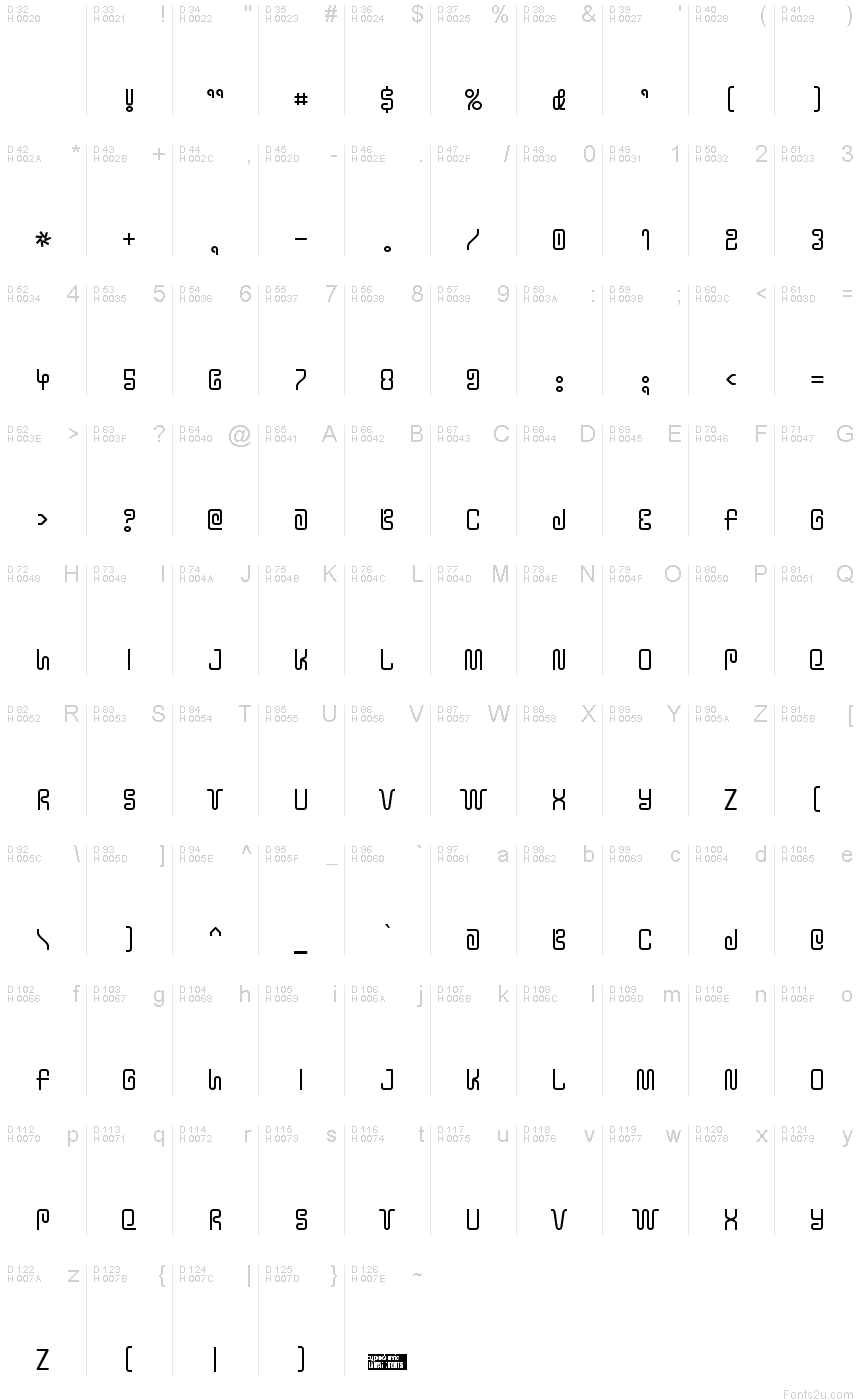
!Y2KBUG
يُعد خط !y2kbug من تصميم Ray Larabie خطاً مجانياً مستقبلياً من نمط العرض (Display)، يبدو وكأنه خرج للتو من شاشة ألعاب قديمة بها خلل تقني. تخلق ضرباته السميكة ذات الخط الواحد، ومنحنياته المربعة، ونهاياته الحلقية إيقاعاً يشبه المتاهة، مما يمنحه طابعاً رقمياً كلاسيكياً (ريترو) وفي الوقت نفسه شعوراً ودوداً بشكل غريب. تتماسك الحروف معاً بتدفق نمطي مُرضٍ، مما يحول الكلمات القصيرة إلى رموز رسومية تبدو وكأنها مبرمجة وليست مكتوبة.
باستخدام !y2kbug، تستقر العناوين في مكانها تماماً مثل عناصر واجهة المستخدم على أجهزة الخيال العلمي القديمة، مما يجعل هذا الخط المجاني خياراً طبيعياً لعناوين الألعاب، ومنشورات الحفلات الصاخبة (Rave) أو النوادي، وهويات الفعاليات التقنية، وملصقات الخيال العلمي، والمنتجات التجارية، والشعارات الجريئة. يعمل الخط بأفضل حالاته في الأحجام الكبيرة حيث يمكن للزوايا المستديرة والهندسة المحكمة أن تبرز جماليته؛ أما في النصوص الصغيرة، فقم بإقرانه بخط هندسي بسيط بلا زوائد (Sans) للحفاظ على الوضوح.